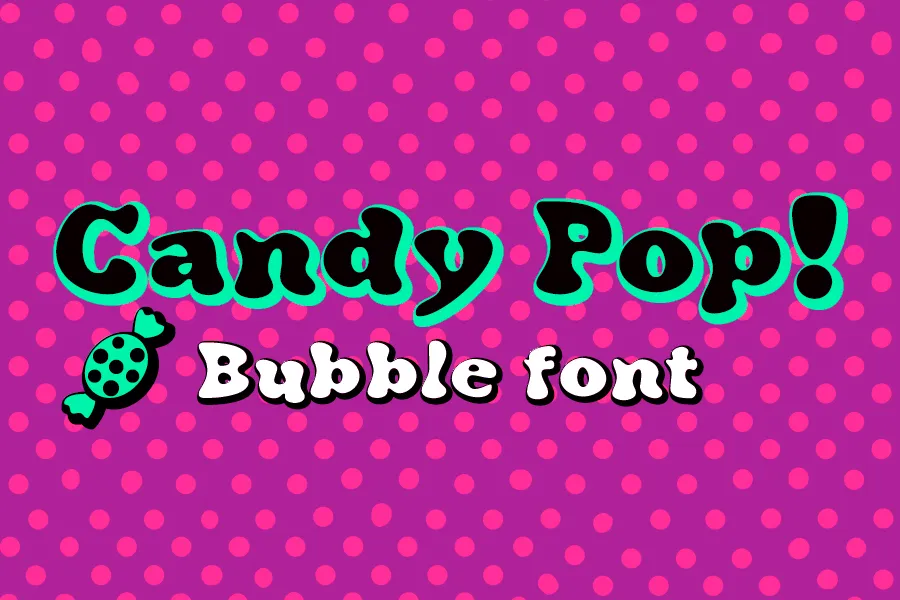
Candy Pop! é uma elegante tipografia que oferece um toque divertido e vibrante para qualquer projeto visual. Este tipo de face de traço rústico traz formas orgânicas com estilos psicodélicos e pop, criando designs arredondados e desiguais. Suas formas sem contorno firme, conhecidas como “bezels”, tornam o Candy Pop! uma opção incrível para usar em títulos ou até mesmo adicionar cores extras nas suas criações multicoloridas. Ideal tanto para posteres e folhetos quanto para anúncios atraentes, este tipo de fonte oferece um projeto divertido que pode ser realizado facilmente no Photoshop. Se você está procurando por uma fonte deslumbrante e única que vai fazer seu trabalho soar mais interessante e animado, não tenha dúvidas, Candy Pop! é o caminho a seguir.